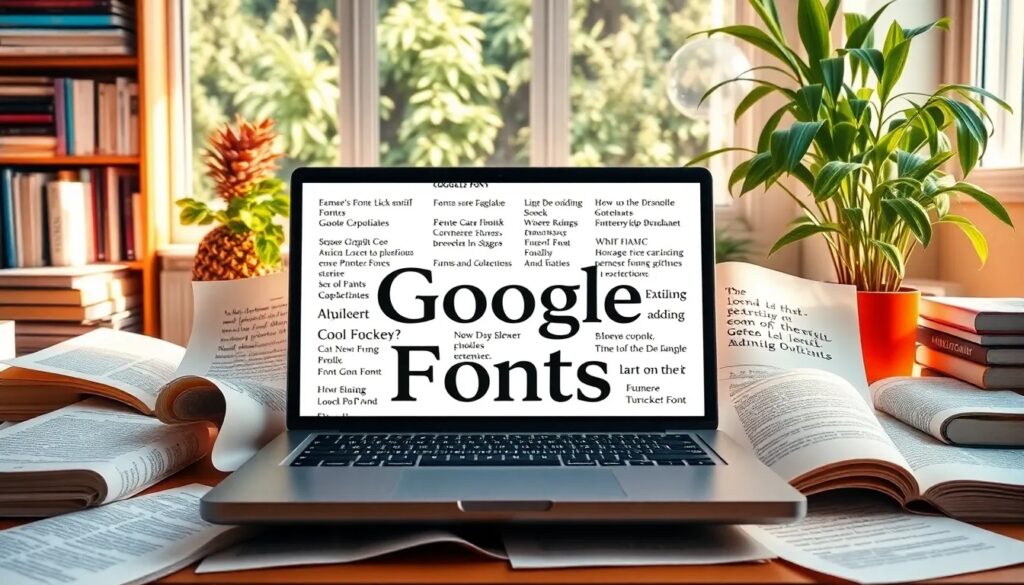
Google Fonts: cómo utilizarlas en tus proyectos
Google Fonts se ha convertido en una herramienta esencial para diseñadores y desarrolladores web que buscan tipografías de alta calidad. Esta plataforma ofrece una amplia variedad de fuentes que pueden ser utilizadas de manera sencilla y efectiva en distintos tipos de proyectos. En este artículo, exploraremos todo lo que necesitas saber sobre Google Fonts.
Desde su funcionamiento hasta las mejores fuentes disponibles, aquí encontrarás información valiosa para mejorar tus diseños y la experiencia del usuario en tus sitios web.
¿Qué son Google Fonts?
Google Fonts es una biblioteca de fuentes de código abierto que ofrece una amplia gama de tipografías para su uso en proyectos web. Esta plataforma proporciona acceso gratuito a fuentes de alta calidad que son ideales para diseño web y aplicaciones. Al ser de código abierto, permite a los diseñadores acceder y utilizar estas fuentes sin costo alguno, lo que las convierte en una opción muy popular.
Una de las grandes ventajas de Google Fonts es su accesibilidad. Con una interfaz intuitiva, los usuarios pueden buscar y filtrar fuentes fácilmente. Esto significa que tanto diseñadores experimentados como principiantes pueden encontrar la fuente perfecta para su proyecto.
Además, Google Fonts ofrece una especialización en la tipografía, permitiendo a los usuarios seleccionar estilos, grosores y variantes de cada fuente. Gracias a esta flexibilidad, los diseñadores pueden personalizar la tipografía para que se ajuste al estilo de su proyecto.
¿Cómo utilizar Google Fonts en tus proyectos?
Además, Google Fonts permite la personalización a través de CSS, lo que significa que puedes ajustar características como el tamaño, el peso y el estilo, para adaptarse perfectamente a tus necesidades de diseño.
¿Cuáles son las mejores fuentes en Google Fonts?
Existen muchas fuentes destacadas en Google Fonts. Algunas de las más populares incluyen:
- Roboto: Una fuente moderna y versátil, perfecta para una variedad de aplicaciones web.
- Lato: Ideal para textos legibles y de aspecto limpio.
- Open Sans: Una opción amigable y profesional que se adapta bien a cualquier contenido.
- Montserrat: Con un estilo geométrico, es perfecta para títulos y encabezados.
- Oswald: Una fuente condensada ideal para diseños llamativos.
Estas fuentes no solo son visualmente atractivas, sino que también han sido optimizadas para una carga rápida en la web, lo que mejora la experiencia del usuario. Al elegir fuentes para tu proyecto, es crucial considerar su impacto en el diseño y la legibilidad.
- Selecciona la fuente en Google Fonts.
- Haz clic en el botón "Descargar" que aparece en la esquina superior derecha.
- Descomprime el archivo descargado y encontrarás los archivos de fuente listos para usar.
Una vez descargadas, puedes incluirlas en tu proyecto utilizando @font-face en CSS. Esto es particularmente útil si decides autohospedar fuentes en tu servidor.
¿Cómo contribuir con nuevas fuentes en Google Fonts?
Contribuir nuevas fuentes a Google Fonts es un proceso que fomenta la colaboración dentro de la comunidad de diseño. Si deseas ayudar a expandir la biblioteca, puedes seguir estos pasos:
- Visita el sitio web de Google Fonts y accede a la sección de contribuciones.
- Revisa las pautas y requisitos para la presentación de nuevas fuentes.
- Prepara tu fuente utilizando herramientas como Glyphs o FontForge.
- Envía tu fuente para que sea revisada por el equipo de Google Fonts.
Este proceso no solo ayuda a enriquecer la oferta de fuentes, sino que también permite a los diseñadores mostrar su trabajo a una audiencia más amplia.
¿Qué licencias utiliza Google Fonts?
Google Fonts utiliza principalmente dos tipos de licencias para sus fuentes: la SIL Open Font License y la Apache License 2.0. Estas licencias permiten a los usuarios utilizar, modificar y distribuir las fuentes de manera libre.
Es importante revisar las especificaciones de cada fuente, ya que algunas pueden tener restricciones específicas. Sin embargo, en general, las fuentes de Google son seguras para su uso en aplicaciones comerciales y proyectos personales.
En resumen, Google Fonts es una herramienta poderosa que ofrece una variedad de opciones para mejorar el diseño de tus proyectos web. Gracias a su accesibilidad, amplia selección de fuentes y facilidad de integración, es una opción ideal para cualquier diseñador o desarrollador.